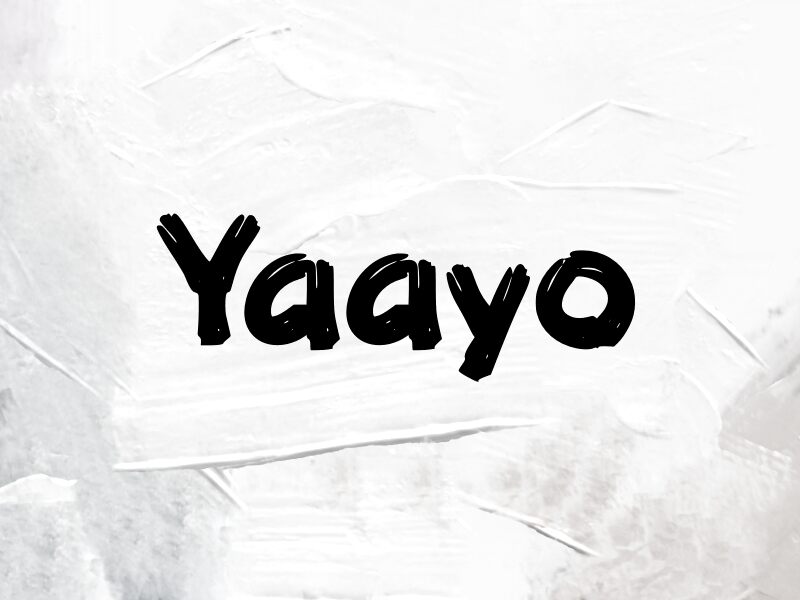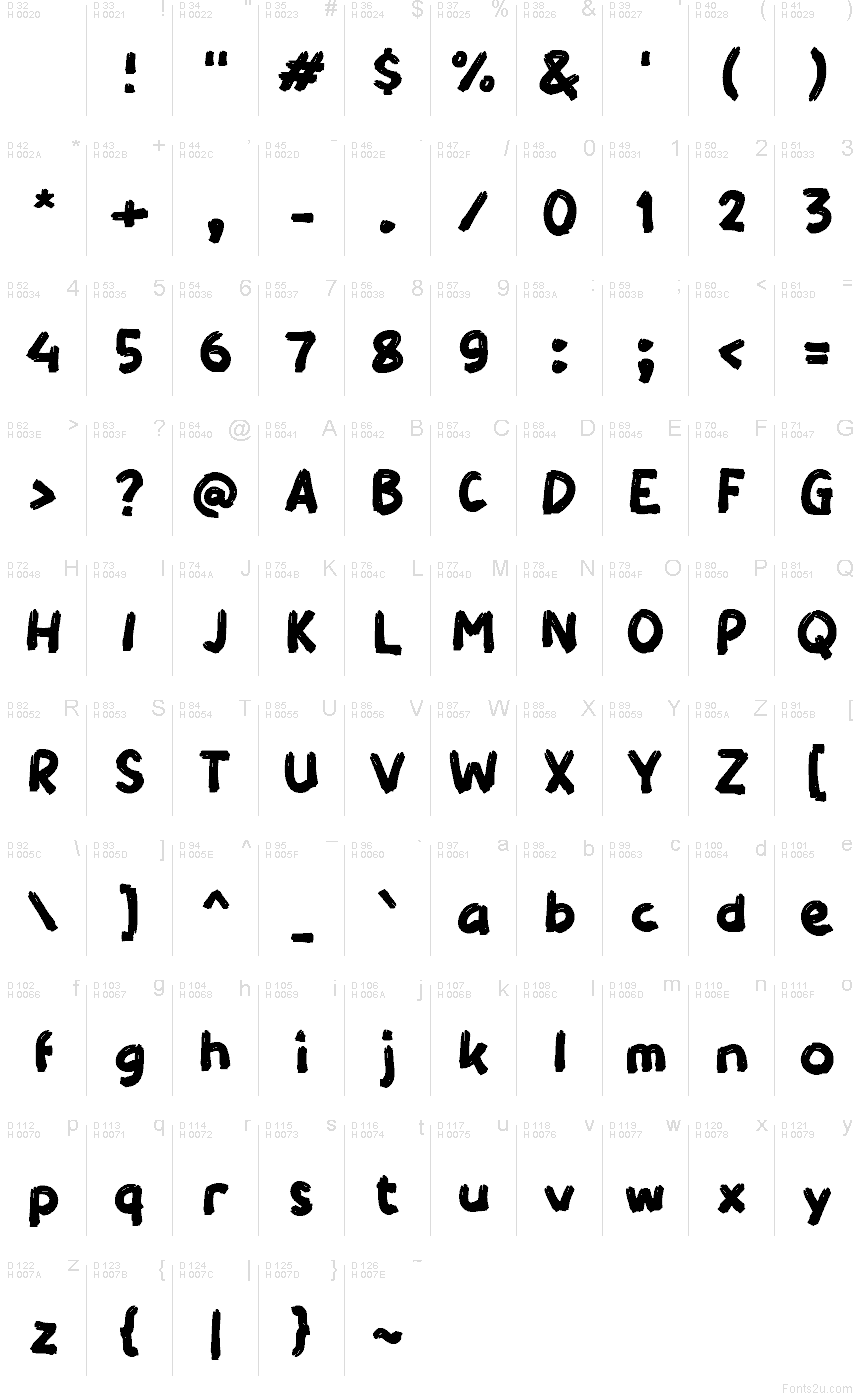
Yaayo
Yaayo da Wep é uma fonte brush gratuita moldada por pinceladas largas e uma textura deliberadamente áspera e sobreposta. O lettering parece ter sido pintado rapidamente com um pincel bem carregado, mantendo as formas escuras arredondadas e densas, enquanto as bordas se fragmentam em pequenas estrias e sobreposições.
Isso torna a Yaayo a escolha natural para títulos de cartazes, arte musical, embalagens, sinalização de cafés e gráficos para redes sociais que exigem uma estética pintada à mão, fugindo do visual script convencional. O ritmo do pincel texturizado confere a títulos curtos e logotipos a presença bruta necessária para marcas de streetwear ou branding de eventos.